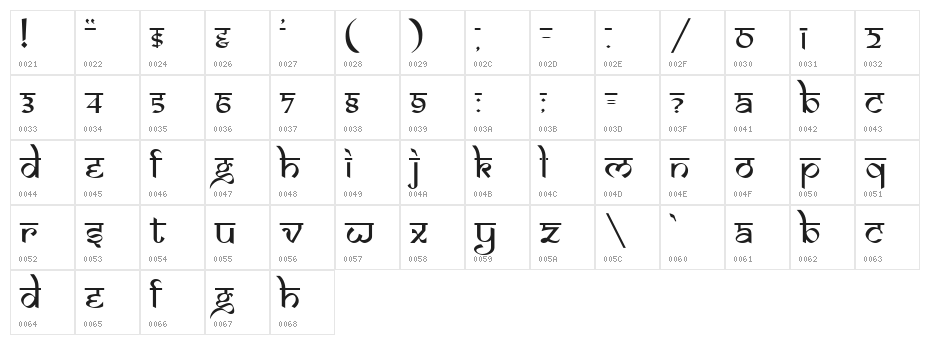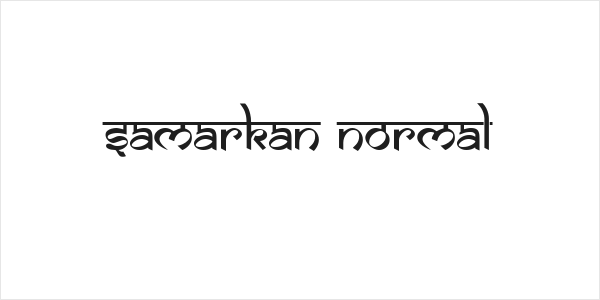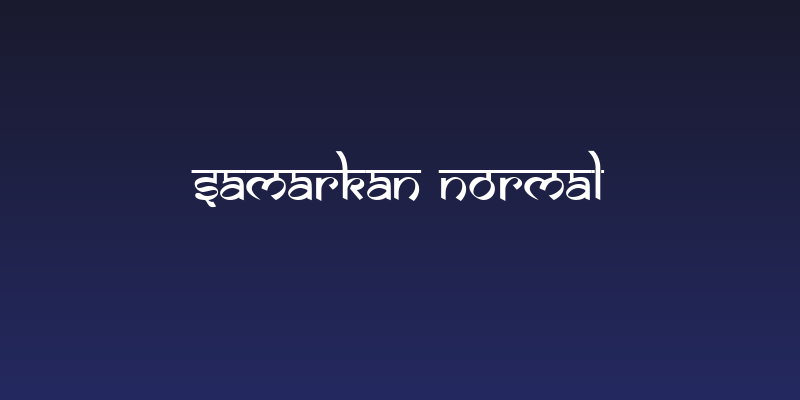
Samarkan Normal Font
| Рекомендуемые проекты | Ideal for projects that require a touch of elegance and cultural flair, such as event invitations, posters, and branding for artistic or cultural events. |